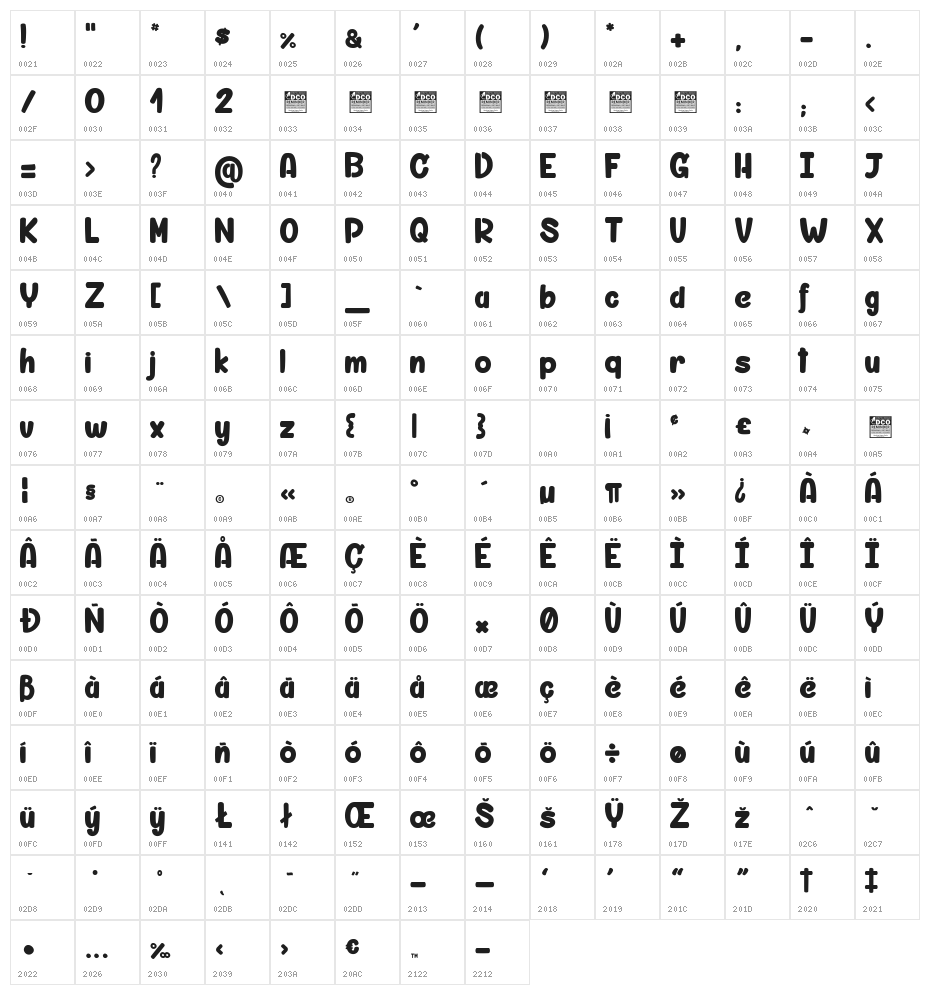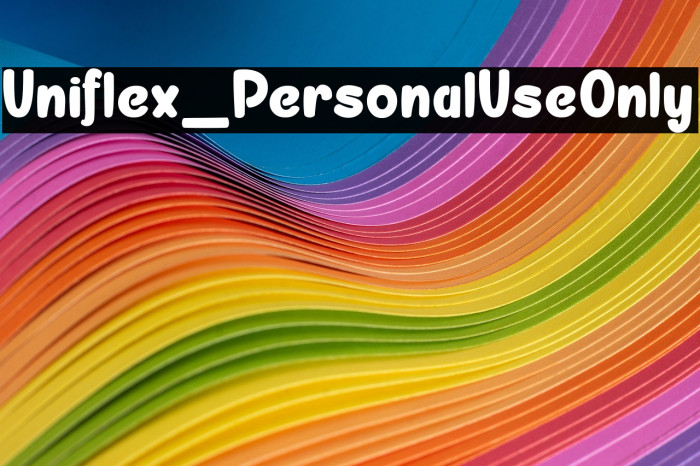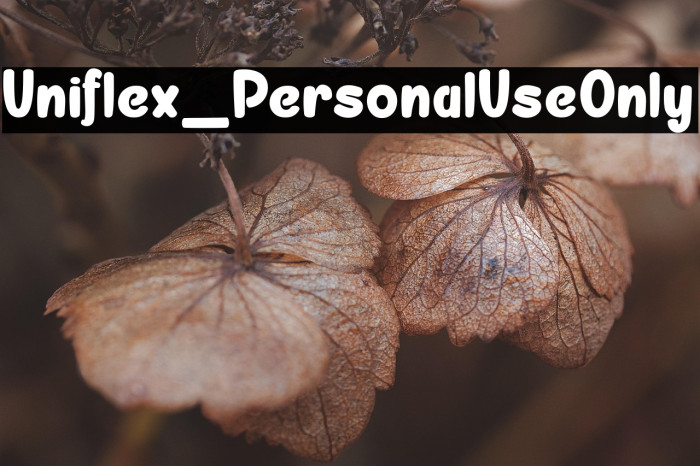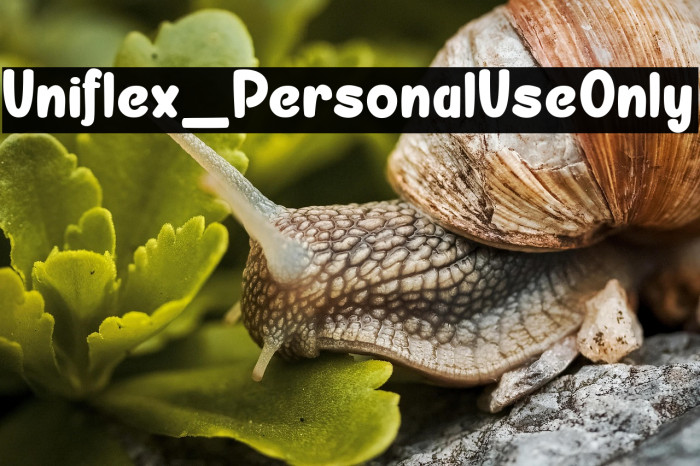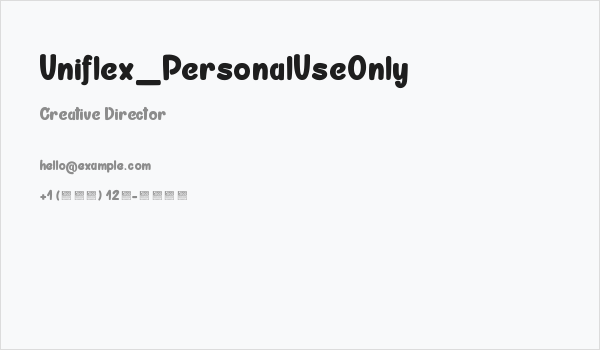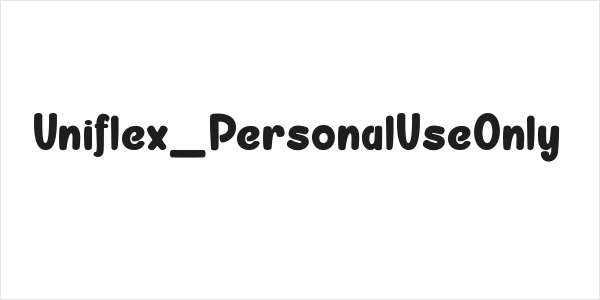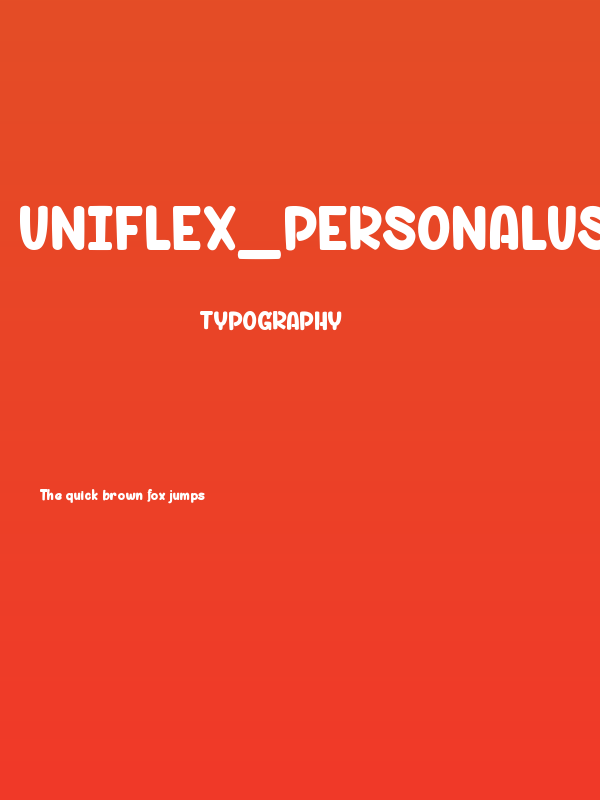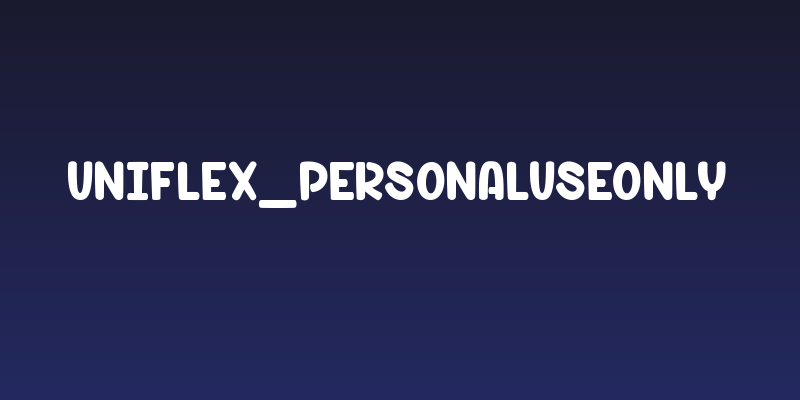
Uniflex_PersonalUseOnly Font
| चौड़ाई | Condensed |
| समग्र शैली | Playful, Modern |
| उपयोग का मामला | Headlines, Logos, Posters |
| सुझाए गए प्रोजेक्ट | Ideal for children's books, playful branding, posters, and any design requiring a fun and approachable tone. |